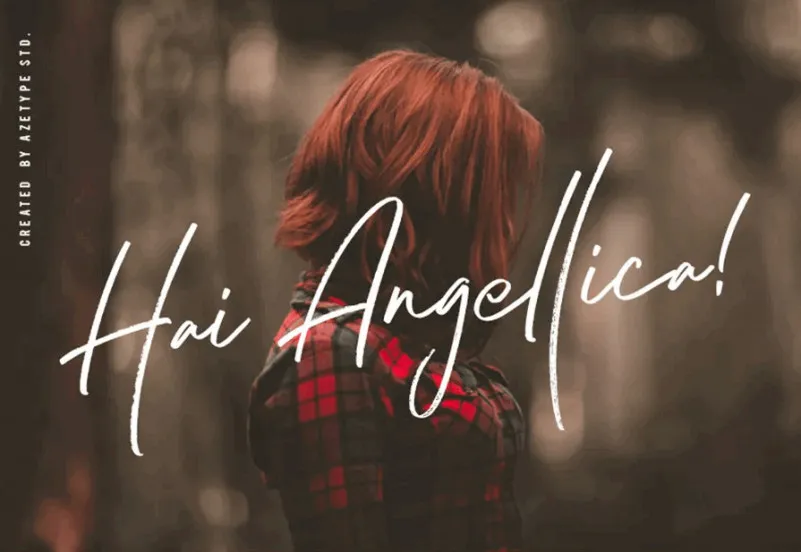
Hai Angellica Handwritten Font – Download Grátis
Aqui está a descrição no formato solicitado: Obrigado por acessar a fonte Hai Angellica Handwritten Font! Esta elegante e criativa fonte foi criada pela Azetype, um estúdio conhecido pelos seus designs meticulosos de letra cósmica. Hai Angellica é uma tipografia feita à mão que combina um estilo de assinatura com um ar romântico e autêntico. Ideal para qualquer aplicação onde desejas transmitir uma personalidade única ou um toque delicado, como logotipos, adesivos de nome, citações escritas a mão, embalagens de produto, materiais promocionais, mídia social e cartões de cumprimentos. Com seu conjunto completo de letras maiúsculas e minúsculas, um amplo espectro de pontuação, numerais e suporte multilíngue, Hai Angellica é perfeita para criar mensagens que despertam emoções. Seja você designer gráfico, publicitário ou criador de material promocional – Hai Angellica está aqui para oferecer um toque especial a seus projetos. Seja qual for o seu projeto, esta fonte trará uma sensação única e autêntica à sua identidade visual. Descubra por si mesmo como ela transforma textos simples em obras de arte!